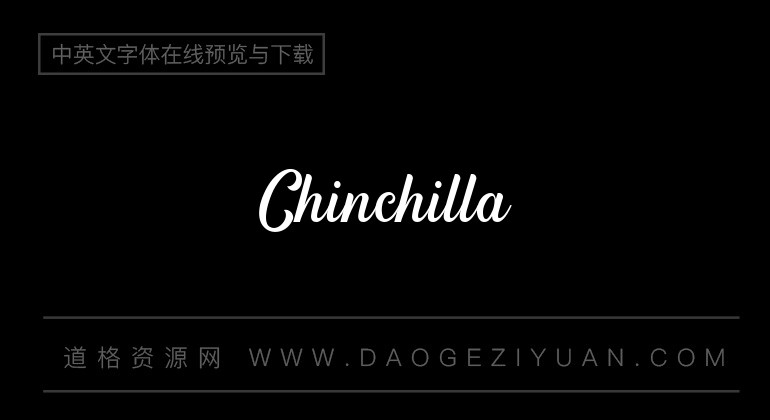
Chinchilla 是一种新的设计字体,它的特点是每个字母都有自己独特的形状,它拥有一种温暖的气息,有助于增强用户体验。它的设计理念是通过把每一个字母都设计成有趣的形状,来增加文字的可读性,以及让字体更加有趣,以便吸引更多的用户。它也具有良好的可读性,可以帮助人们更好地阅读文字。内容介绍
Chinchilla是一款非常不错的手写艺术字体,具有很好的视觉感,适合于文化类的宣传设计、商业类品牌的广告和产品包装设计以及个性化文字排版等较多场景。